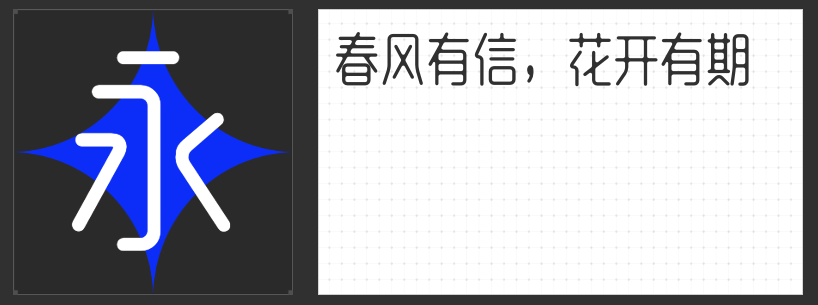
短视频视觉升级指南:四款风格化字体解锁动态叙事新维度
短视频的视觉表达需兼顾瞬间抓眼与情绪延续,字体作为画面中的“无声旁白”,其形态、节奏与风格直接影响观众的情感共鸣。以下四款风格鲜明的字体,以独特的设计语言为短视频注入动态叙事基因,助力创作者打造记忆点鲜明的视觉符号。
一、字恋狂风摇简 粗体
这款字体以“被风吹动的笔触”为灵感,通过夸张的笔画倾斜与比例失衡,营造出摇曳生姿的动态感。歪扭的笔画轨迹与手写质感,赋予文字天然的亲和力,仿佛每一笔都带着创作者的温度。其不规则的笔画粗细与留白设计,在动态画面中能自然吸引视线,适合传递轻松、治愈或富有童趣的内容主题,让文字成为画面情绪的延伸。
二、字恋狂漫野 鸣风
以手写直线为基础,这款字体通过细微的字型大小变化与通透的布白空间,构建出富有呼吸感的节奏体系。去钩处理与笔画断开的设计,既保留了手写的灵动,又避免了视觉杂乱。在短视频中,其均匀的灰度与张弛有度的结构,能适配快节奏剪辑或需要层次感的画面,让文字随镜头切换自然流动,成为串联叙事的关键线索。
三、励字磅礴简 超黑
实验性融合斜体与正体的设计,让这款字体在稳重中暗藏锋芒。左侧倾斜的笔画赋予文字向前冲的动势,右侧垂直结构则夯实视觉根基,形成“万壑争流”的磅礴气势。其强烈的视觉冲击力,适合需要强化品牌调性或传递权威感的短视频内容,如纪录片片头、品牌宣言等场景,让文字成为画面中的视觉锚点。
四、高手庆科静雅体 古朴版
瘦长工整的字型与均匀的布白,赋予这款字体克制而优雅的气质。圆角处理与小连笔设计,让直线结构在刚硬中透出柔和,软硬适中的笔画质感,既适合古典文化类内容,也能为现代简约风格增添细节温度。在短视频中,其平稳的重心与干净的视觉呈现,能有效平衡复杂画面,让文字成为喧嚣中的宁静注脚。